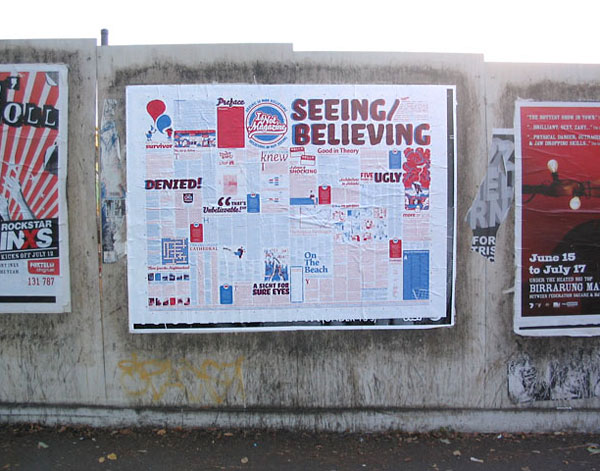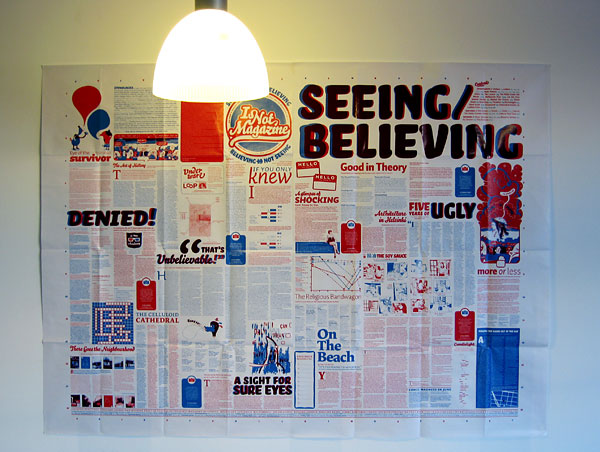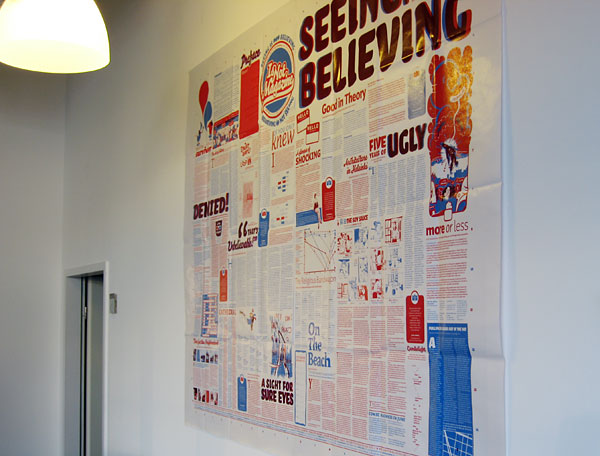
Post von UnderwareWas für eine Überraschung: Drei Quadratmeter
Neujahrsgrüße unserer holländischen Freunde und Partner Underware sind
gerade eingetroffen. Das Großkuvert hat eine weite Reise hinter sich: von
Melbourne über Den Haag bis nach Berlin. Es enthält die Ausgabe 2 der
australischen Wandzeitung »Is not Magazine«. Im August letzten Jahres
hatte ich hier im Fontblog über die
außergewöhnliche Publikation geschrieben. Jetzt ziert eine
Originalausgabe unsere Räume. Weiterlesen ...
Eigentlich ist das Is Not Magazine keine Zeitschrift, sondern ein
Plakat. Aber es ist wie eine Zeitschrift gestaltet und wird auch so gelesen, in
den Straßen von Melbourne, an 50 ausgesuchten Plätzen. Und weil es
überwiegend mit den Schriften von Underware – sehr typografisch
– gestaltet ist, erfreut die Zeitschrift die Augen aller Schriftenfreunde.
Zur Zeit hängt Ausgabe 4 in den Straßen von
Melbourne.
![]() Bis unter die Decke: 1,5 Meter hoch und 2 Meter breit – Ausgabe 2 der australischen Wandzeitung »Is not Magazine« im FontShop-Büro ![]() Die Zeitschrift ist über dem Fotokopierer angebracht, wo sie bei längeren Kopier-Jobs für Zertreuung sorgt ![]() Die Neujahrsgrüße von Underware an FontShop ... auch wir bedanken uns und grüßen mit dieser kleinen Reportage zurück ![]() Premiere in Melbourne: Ausgabe 2 von Is not Magazine an einer öffentlichen Wand in der australischen Metropole (Foto: Is not Magazine) Die gefragtesten Underware-Schriften im Detail: Auto Complete Family (3 x 24 Fonts, drei Kursivformen, Vielfalt plus Komfort), 450 € Bello Complete (6 Fonts, nette Script, kontrastierende Caps), nur 75 € Dolly (sympathische Textschrift mit 4 Schnitten), nur 150 € Sauna Complete (18 Fonts, freche Halbserif mit markanter Italic), 250 € Herausgegeben: Di - Januar 17, 2006 at 10:00 vorm. | |